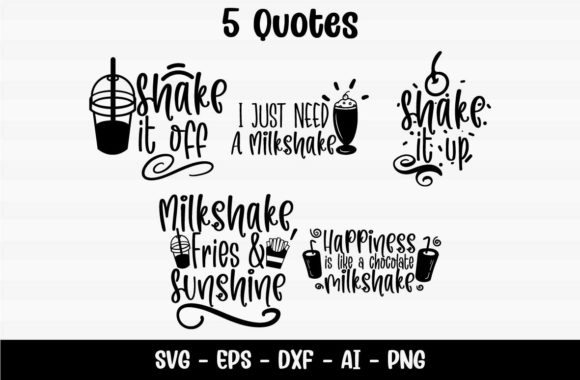
Sweet Milkshake Quotes
Jika Anda mencari aset berkualitas tinggi seperti Sweet Milkshake Quotes, paket premium ini adalah pilihan fantastis untuk proyek kreatif Anda.
Dibuat dengan presisi, Sweet Milkshake Quotes menyediakan vektor yang bersih, tipografi yang halus, serta lisensi komersial untuk ketenangan pikiran Anda.